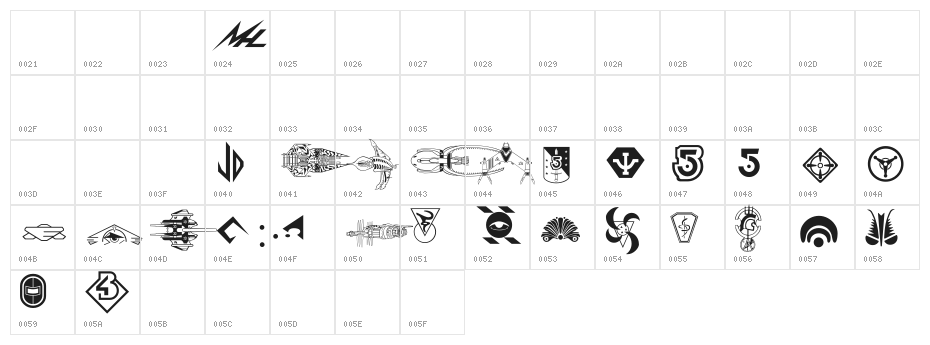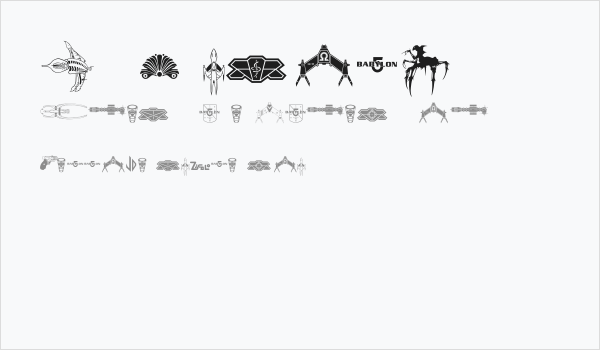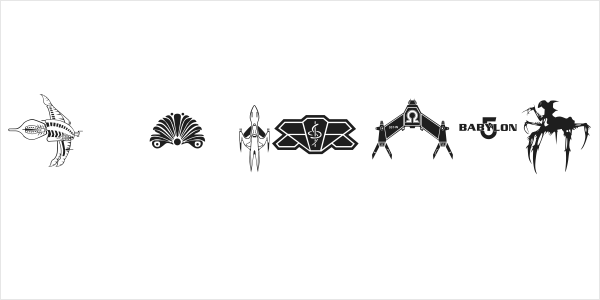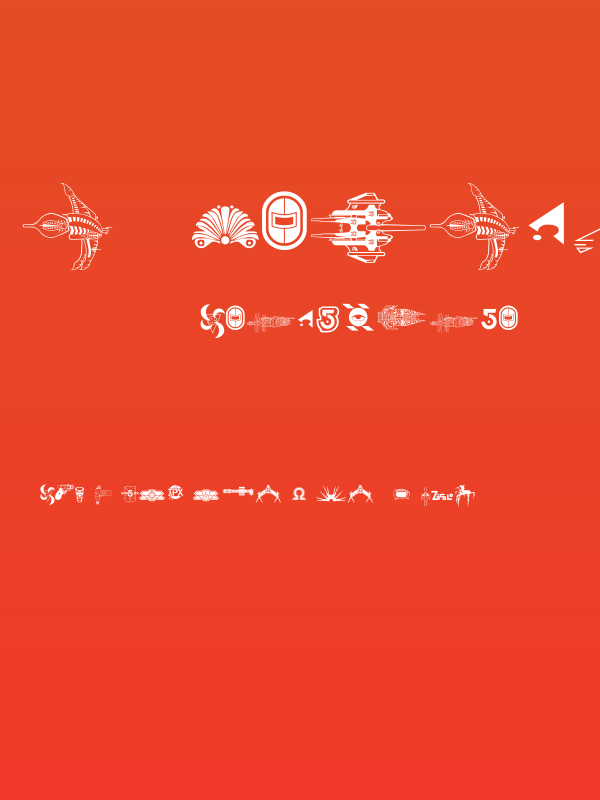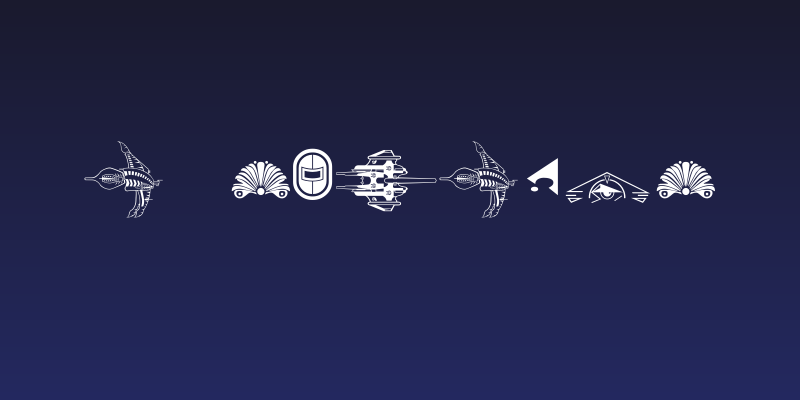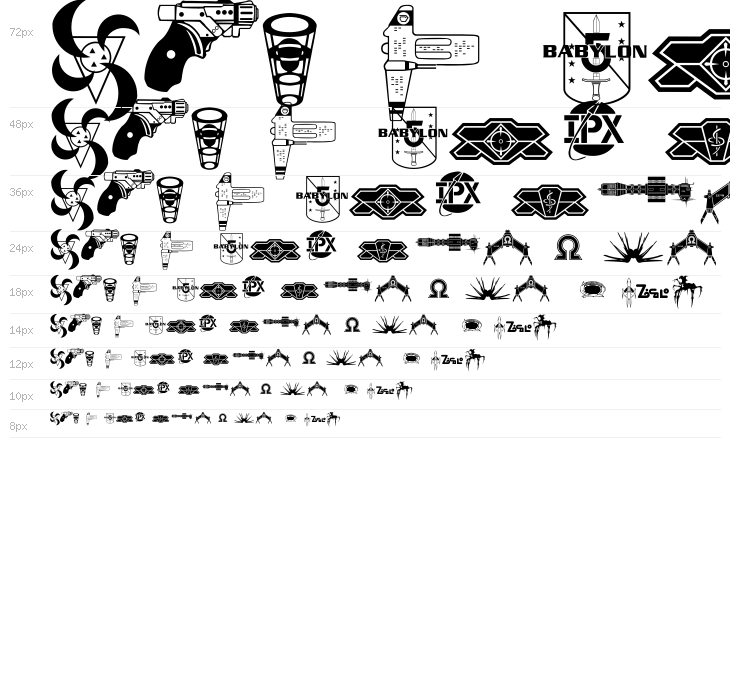
B5Symbols Font
| Stile generale | Futuristic, Decorative, Sci-fi |
| Caso d'uso | Logos, Posters, Game UI, Themed Graphics |
| Progetti proposti | Ideal for science fiction projects, game interfaces, posters, branding for tech or entertainment, and creative digital artwork. |